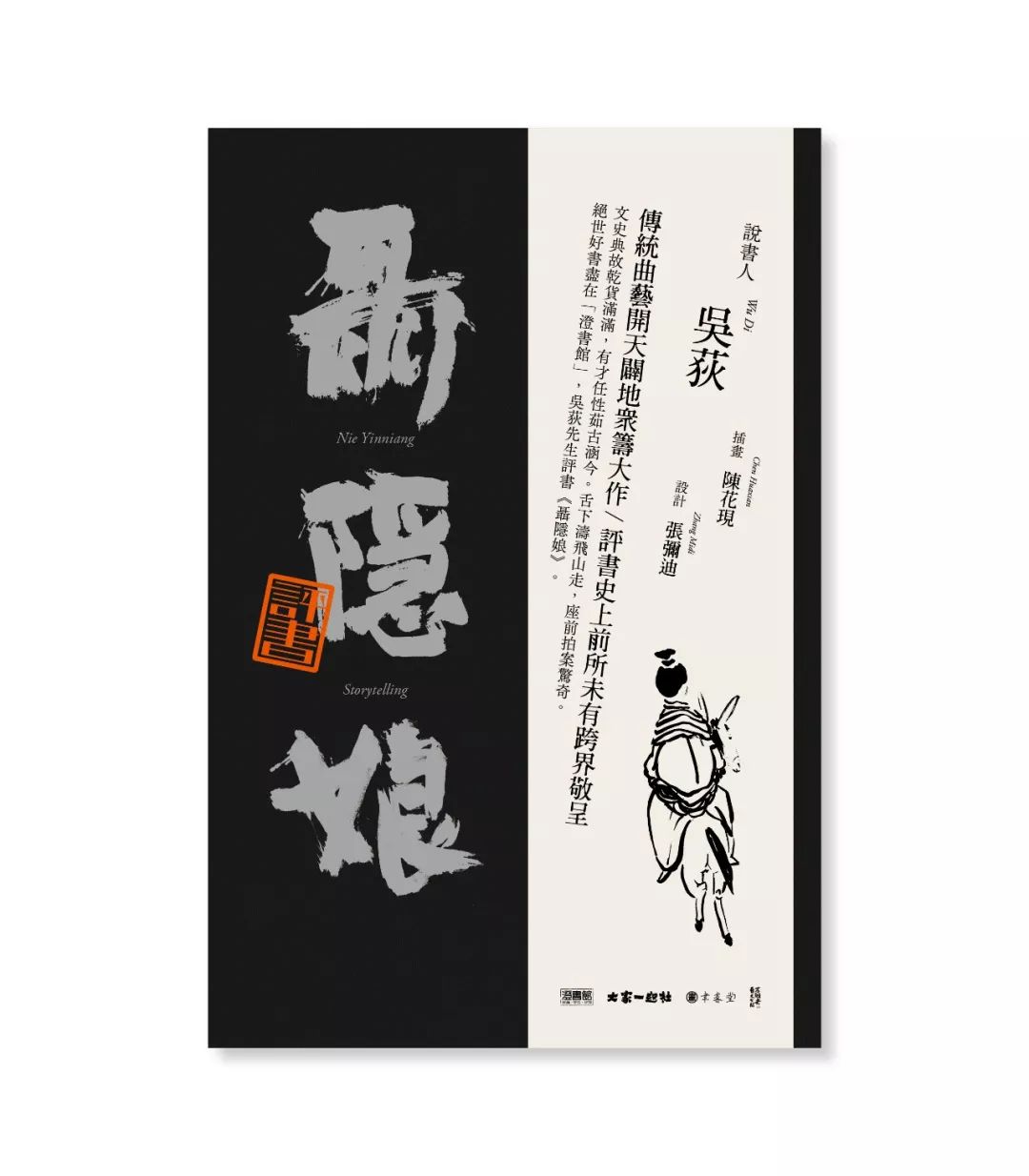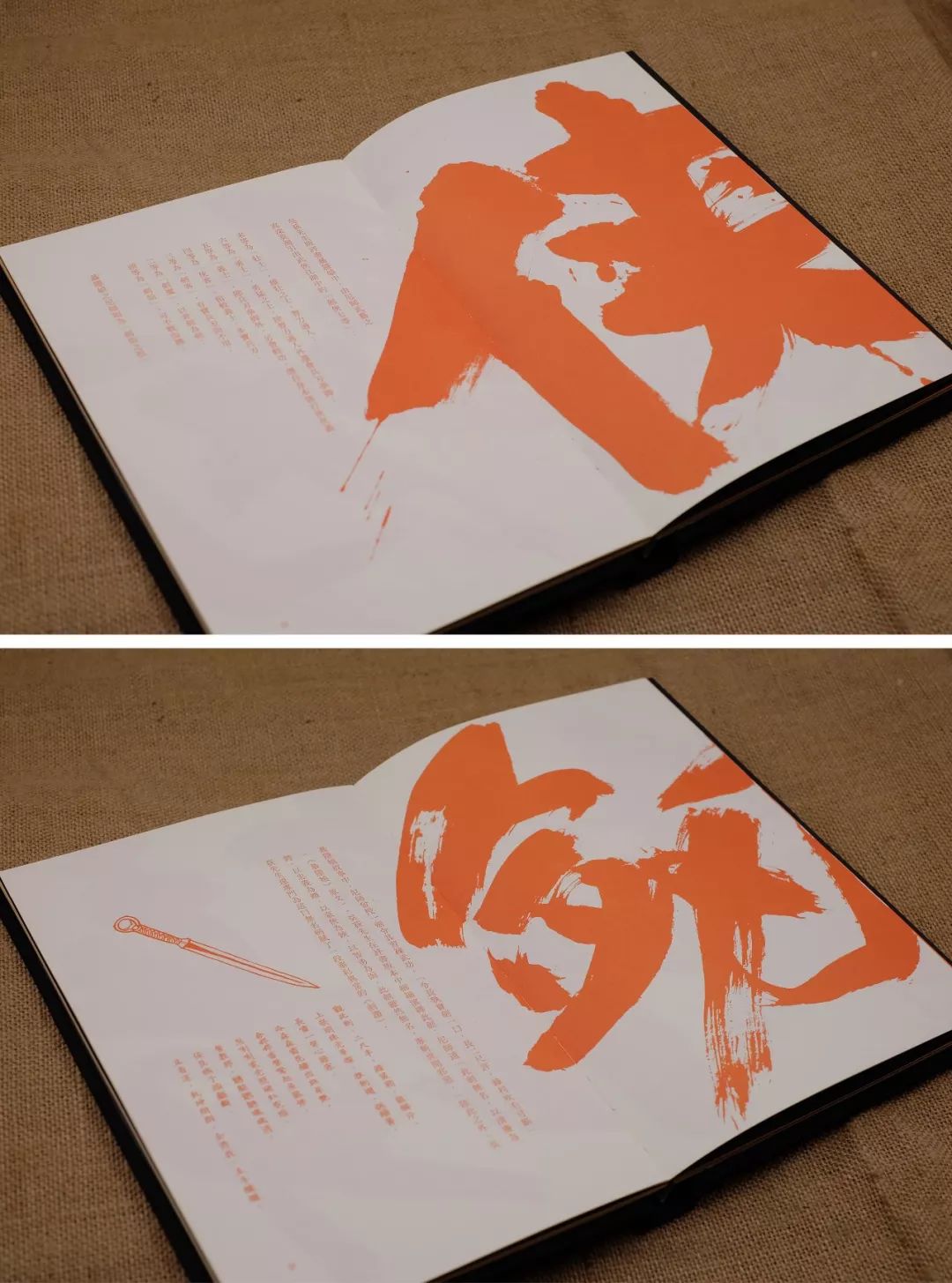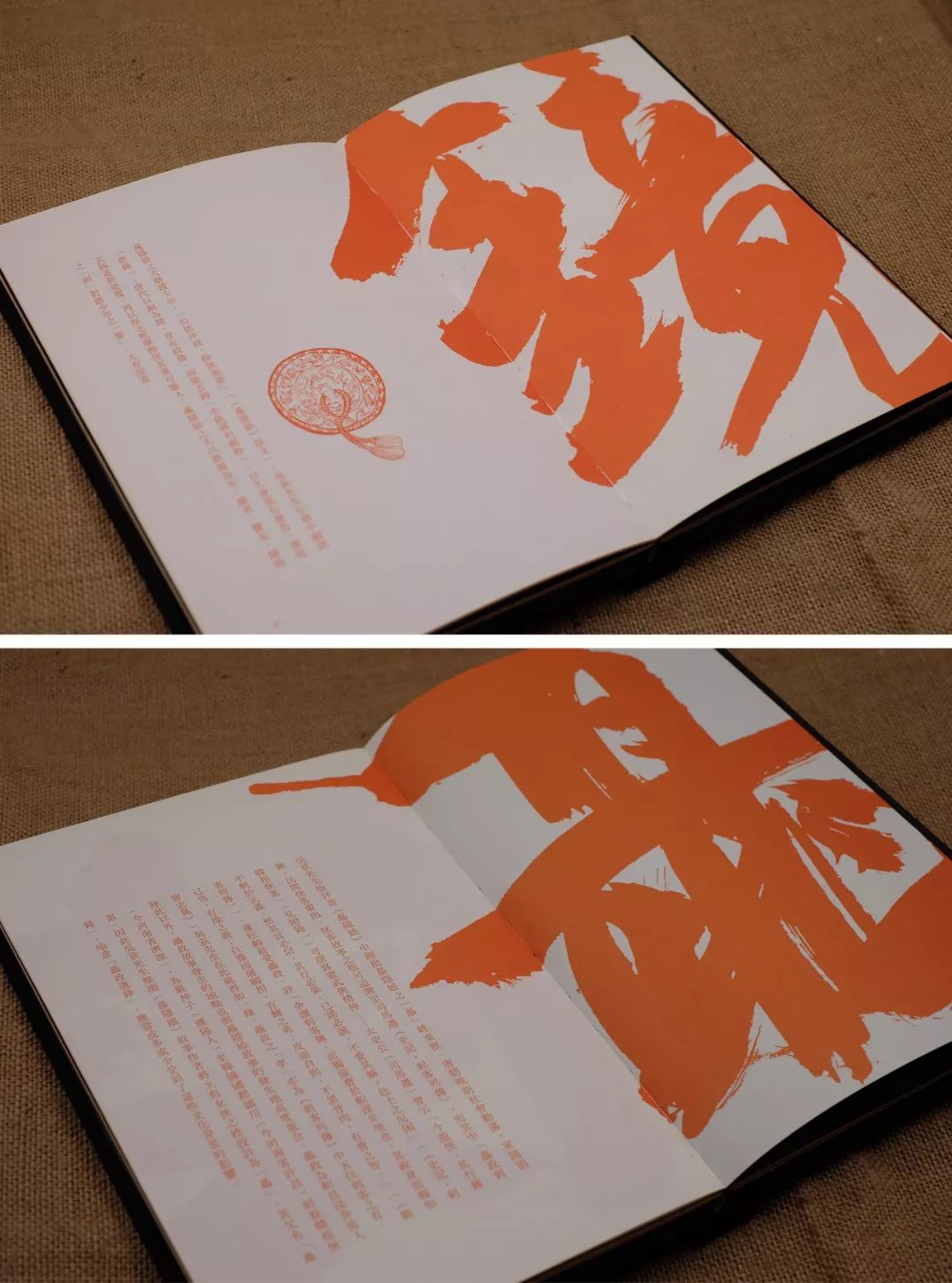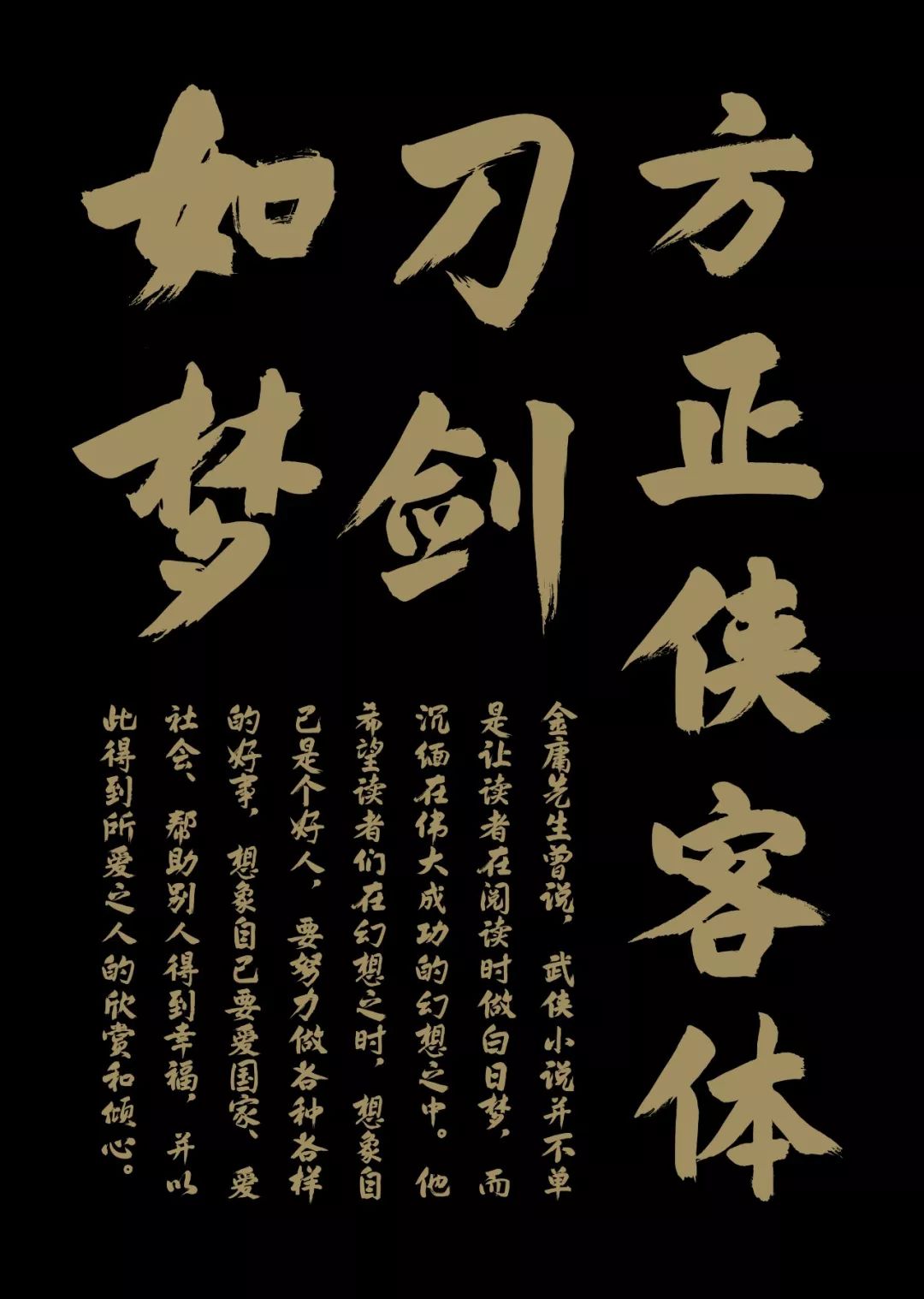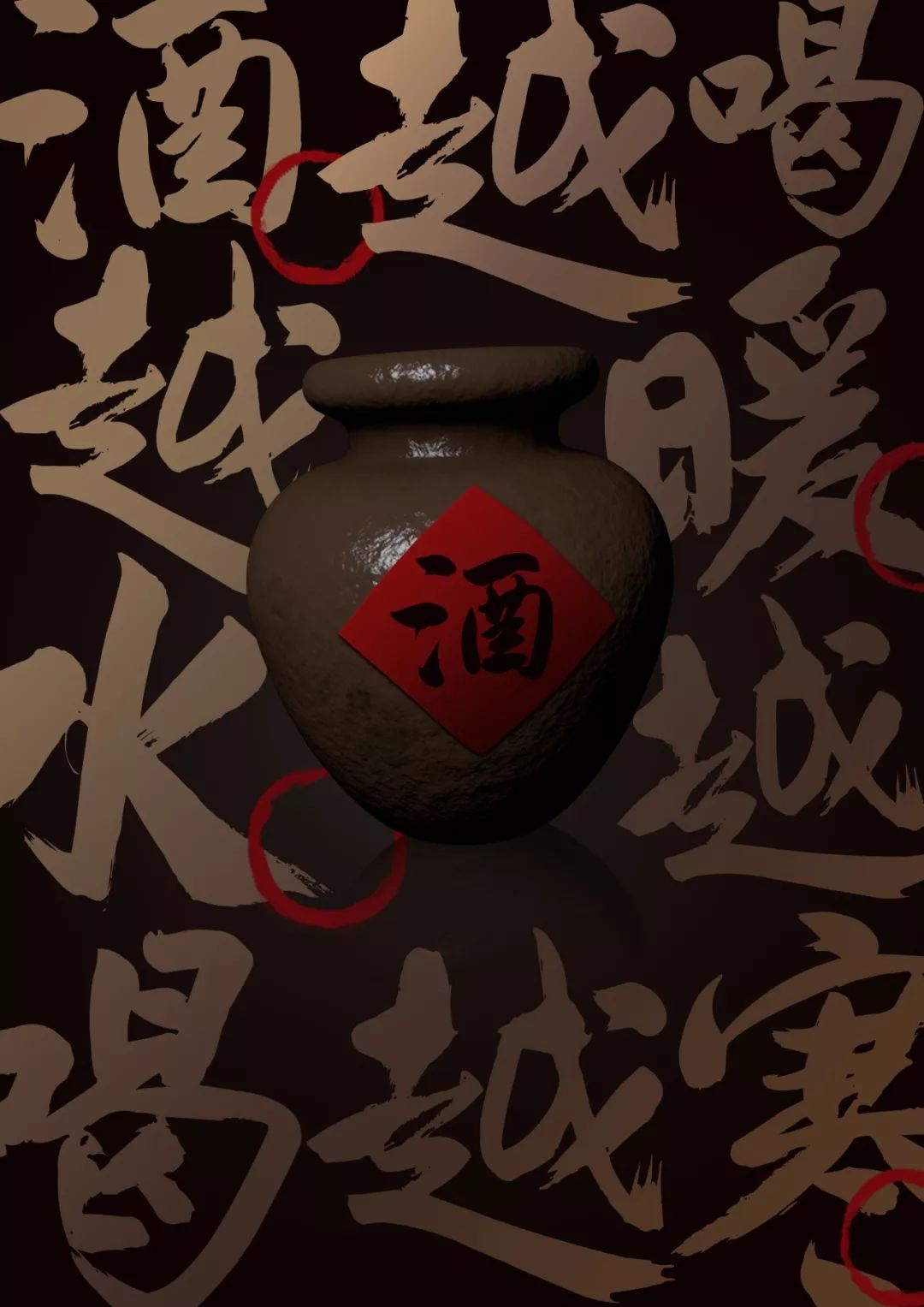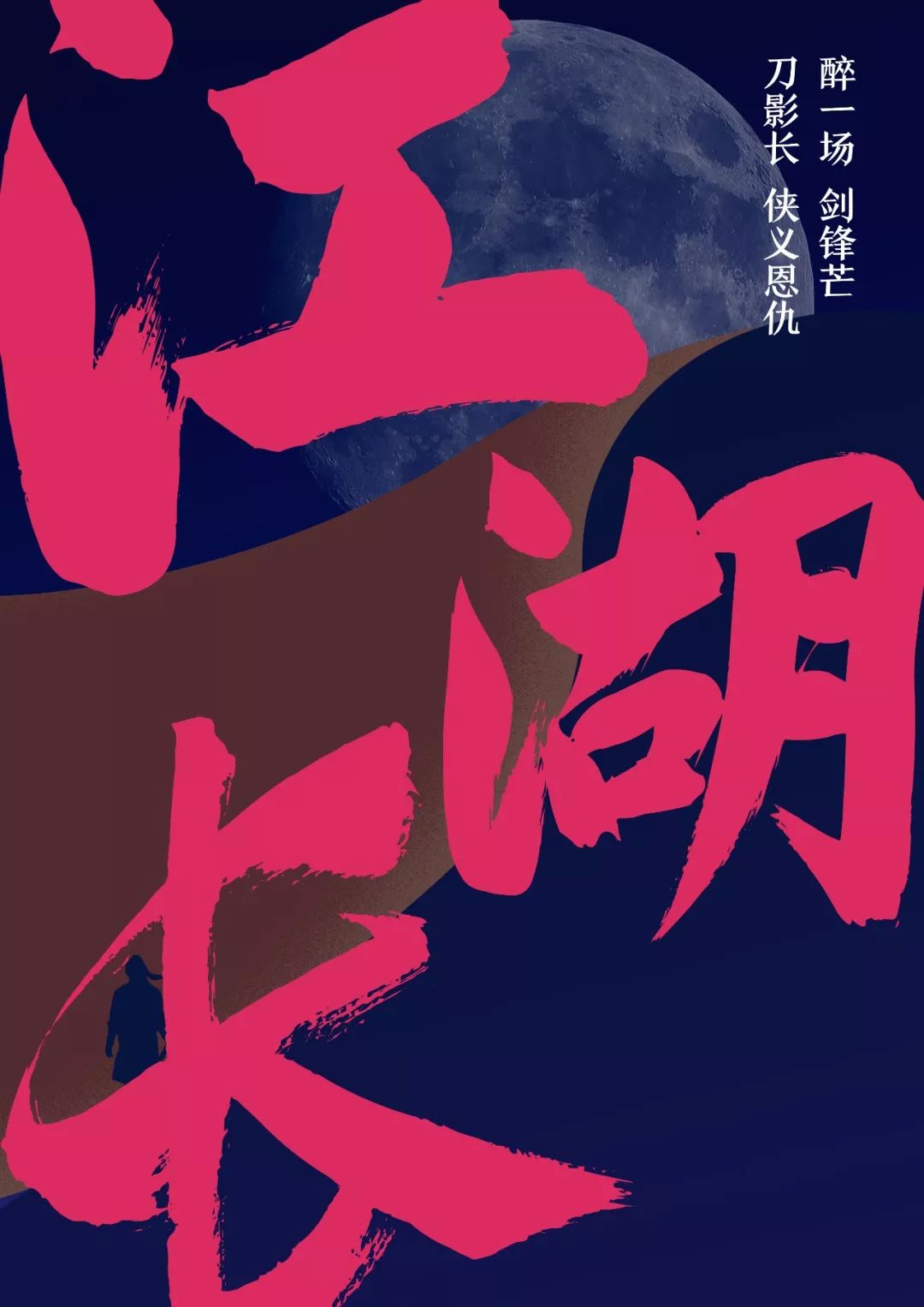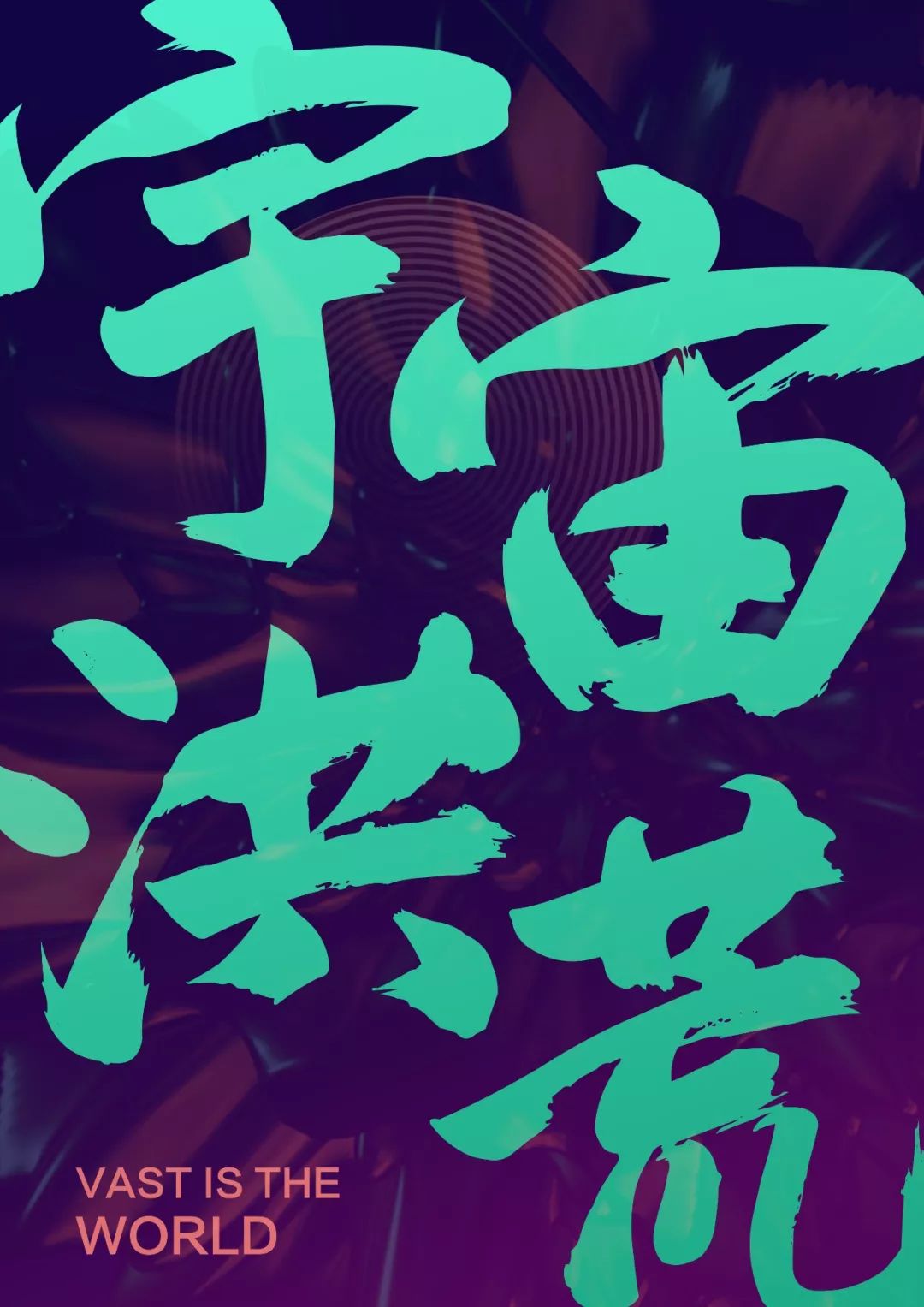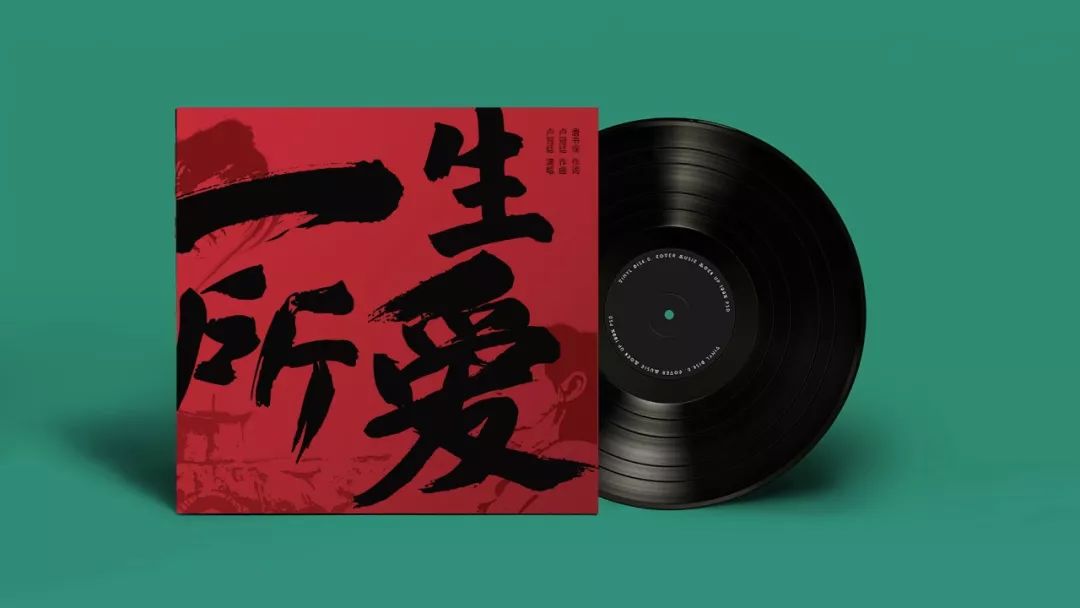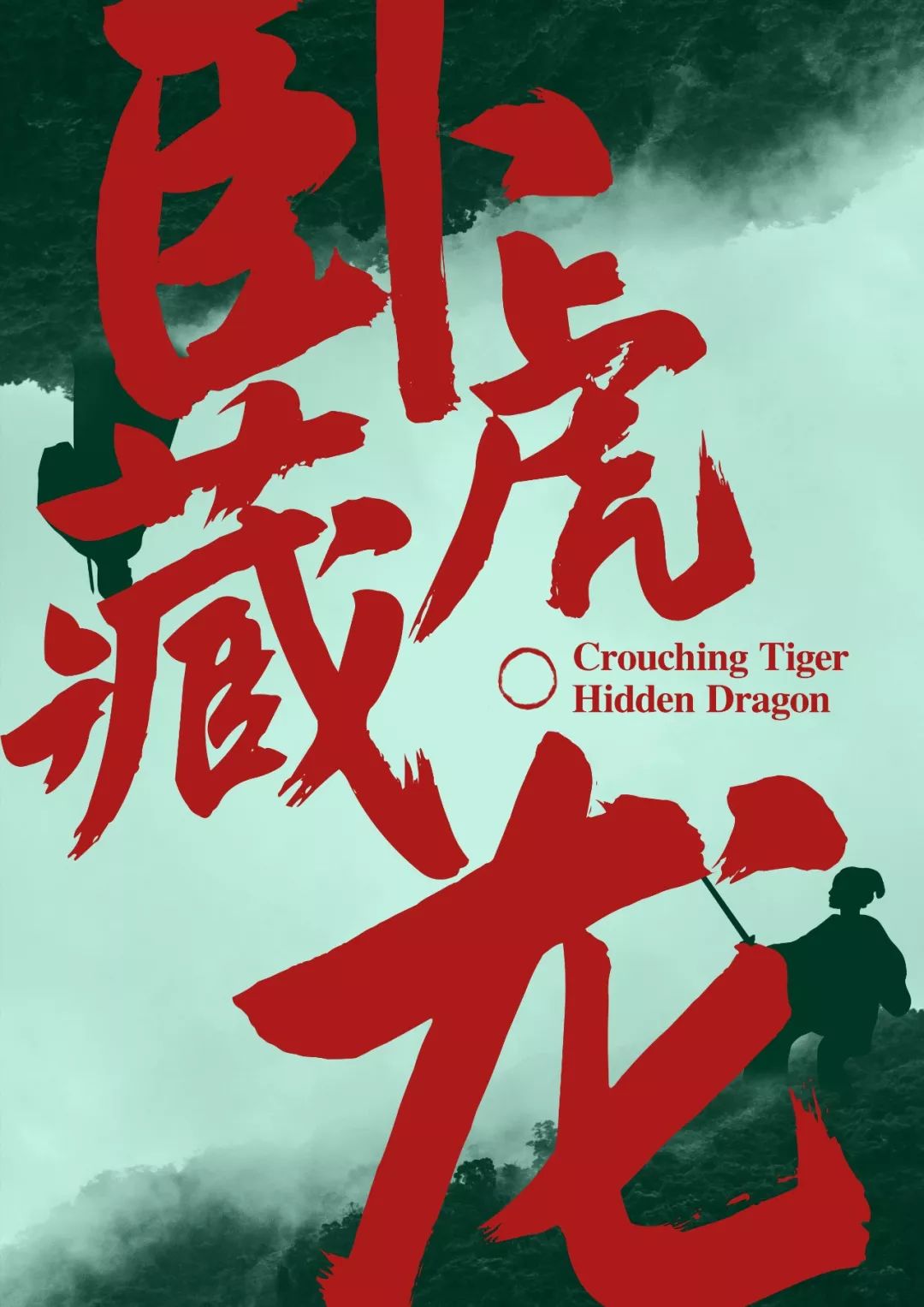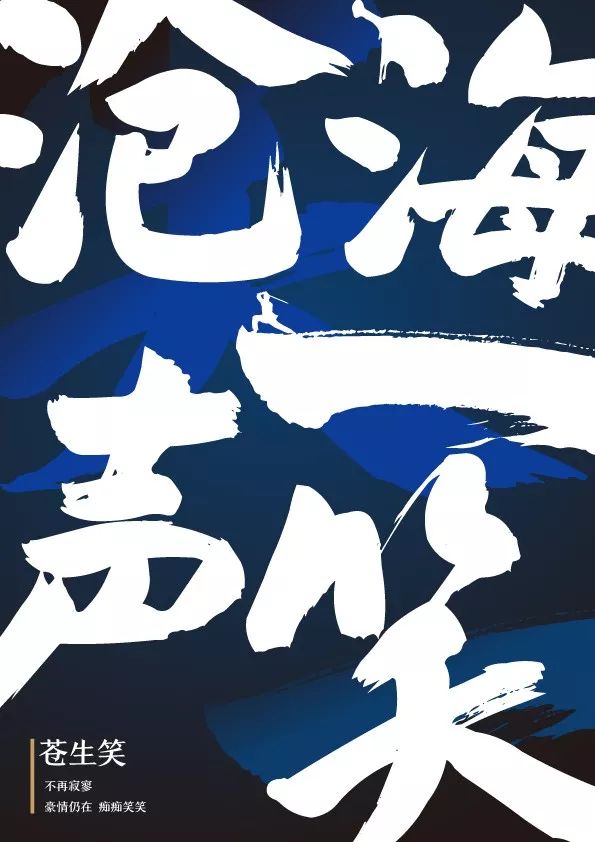
方正侠客体
方正侠客体的创作源自设计《评书聂隐娘》出版物,写字如挥剑,讲究轻重缓急,当时希望用这种斩钉截铁的率性书写来呈现侠客的潇洒与果敢。 古人云:“随心所欲不逾矩”,我们必须尊重传统、敬畏传统,在此基础上创作出具有时代特色的作品,侠客体的创作就是基于这样的理念。师法古代经典碑帖,比如颜真卿、张即之、朱熹等名家作品,字形以行楷为基准,尽可能保留笔画的丰富性,比如粗细变化、相同偏旁部首的变化以及飞白的效果等。作者希望创作一种既符合传统书法的笔法与结构,又能具有视觉设计张力的书法标题字体。主要适用于广告、包装、影视剧的标题等。
很多人心中都有一个武侠梦。骑最烈的马,舞最快的剑。快意恩仇,潇潇洒洒。张弥迪也亦然。不同的是,他以笔代剑,用9664个字书写出心中的武侠梦。
从小临习书法的平面设计师张弥迪是一个侠心不死的人。不同的是,别人刷武侠剧时,他更喜欢用自己的毛笔把侠客风范“演绎”在宣纸上。毕业之后的张弥迪,工作主要以书籍、标志设计为主。但热爱书法的他,也一直没有间断过书法练习,并不断尝试将书法用于适合的设计项目。正如电影《英雄》中的残剑,能把剑法融入书法一样,张弥迪以笔代剑,用斩钉截铁的率性书写,来呈现侠客的潇洒与果敢。在2016年着手设计《评书聂隐娘》时,他创造性地结合武侠与禅宗,草创了一款“禅侠字体”。
古人云:“随心所欲不逾矩”,尊重传统、敬畏传统,在此基础上创作出具有时代特色的作品。方正侠客体的创作就是基于这样的理念——师法古代经典碑帖,如颜真卿、张即之、朱熹等名家作品,字形以行楷为基准,尽可能保留笔画的丰富性,比如粗细变化、相同偏旁部首的变化以及飞白的效果。创作一种既符合传统书法的笔法与结构,又能具有视觉设计张力的书法标题字体。
方正侠客体样张“侠客体”更强调运笔写字时的抑扬顿挫、轻重缓急需发于心。这样的字体摆在面前,若用“好看”来评价,则有轻佻之嫌,更贴切的评价是一个字即为一场充满侠气的修行。